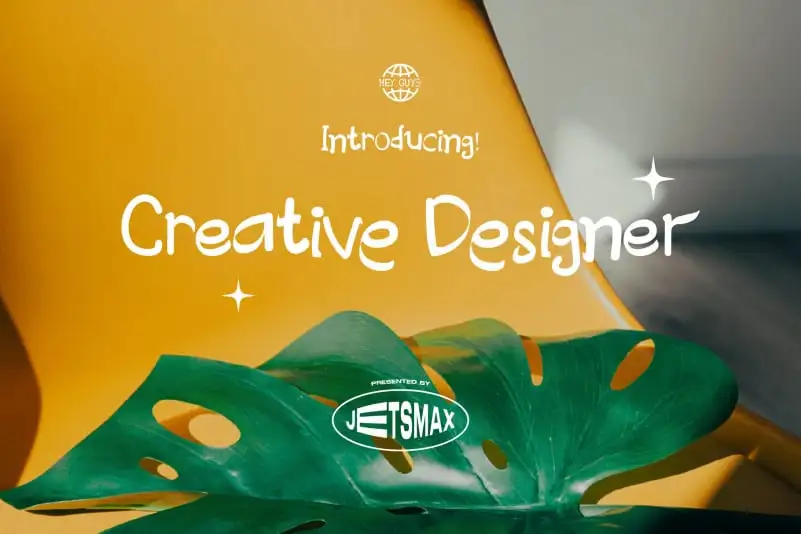
Creative Designer Font – Fonte Grátis
Creative Designer Font
Creative Designer Font é uma fonte que representa você, a pessoa criativa que vive dentro do seu cérebro, sempre com novas ideias inovadoras. Este design exclusivo combina o estilo delicado de traçados livres e escrita manuscrita, dando um toque genuíno de look dançante às suas criações. Este recurso único faz da Creative Designer Font uma escolha perfeita para designers que desejam dar vida a seus projetos com energia vibrante e originalidade inconfundível. Composta por cores vibrantes e linhas fluidas, esta fonte não apenas ajuda a destacar seu trabalho, mas também transmite sua personalidade única através de cada letra. Se você procura uma maneira de expressar-se artisticamente e dar vida ao seu design com o toque perfeito do artista dentro de si, Creative Designer Font é um excelente investimento.
Designer: jetsmax